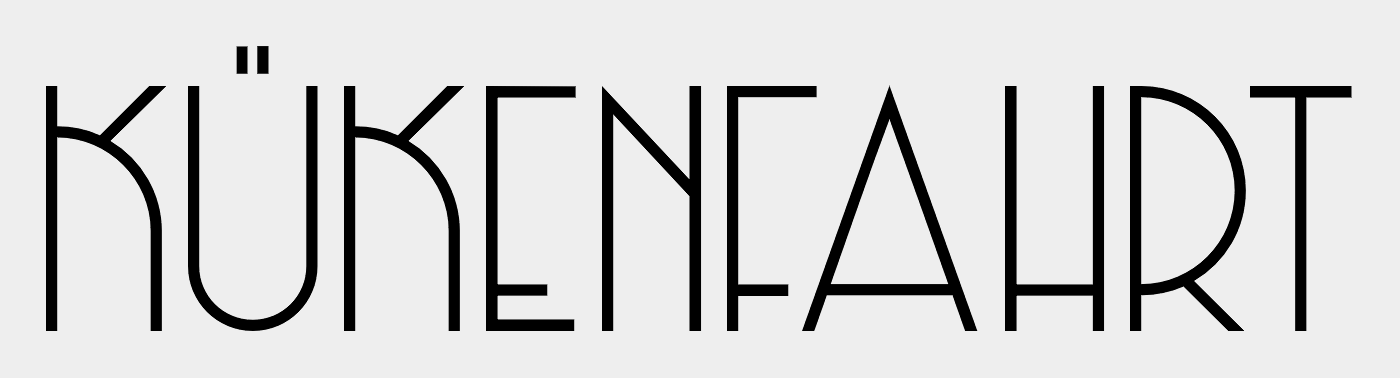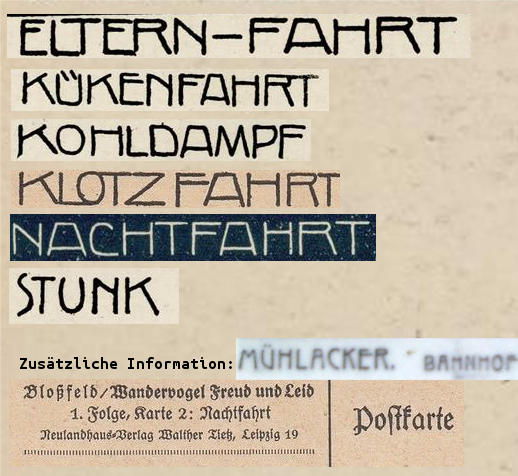
Suche: Satzschrift ca. 1920, Postkarten und Bild-Beschriftungen
leider komme ich bei der Suche - u.a. entsprechende der „ besten Tricks“ - nach einer Schriftart nicht weiter. Auch das Freistellen einzlner Buchstaben sowie das Entfernen der Unterschneidung hat für die Finde-Tools nichts gebracht. Besonders lässt mich Trick No9 zweifeln ob es sich überhaupt um eine „heute verfügbare Satzschrift“ handelt. Vielleicht kann mir hier jemand weiterhelfen.
Die ersten sechs Worte (siehe Grafik) sind und vermutlich vom selben Verfasser. Sie finden sich auf (Scherenschnitt!-)Postkarten aus den Jahren um/vor 1920 und stammen aus einem Verlag bei Leipzig. Ich bin mir sicher dass ich diese Art von Schrift jedoch auch auf gänzlich anderen Karten/Bildern gesehen habe.
Besonders markant finde ich die Buchstaben A,K, und R. Sowie die Höhe der Querstriche bei E,R und F. Das Bild mit dem Text „M… Bahnhof“ (eine Bildunterschrift) zeigt m.E. trotz Abweichungen eine sehr ähnliche Schrift, ist vermutlich jedoch ca. 5-10 Jahre später (und in Württemberg) entstanden. Die zusätzlichen Informationen habe ich für einen eventuellen Abgleich der Zeit hinzugefügt.
Da beide Quellen vermutlich handschriftlich sind frage ich mich ob es für diese beiden wohl eine gemeinsame Grundlage gibt. Ich bin für jeden Hinweis sehr dankbar.
Ich meine auch, diese Schrift (obwohl die in diesem Beispiel wohl handgezeichnet ist), schon einmal sehr ähnlich in einem früheren Strang (und auch sa sehr sicher handgeschrieben) gesehen zu haben.
Gut möglich, das die Schrift als Vorlage in einem Vorlagenheft für mit der Feder zu schreibende Werbeschriften, und dort sicherlich vom Autor ebenfalls handgeschrieben veröffentlich wurde. Ich habe ähnliche Anleitungshefte, herausgegeben von verschiedenen Schreibfedern-Herstellern und Tinten-Herstellern wie Brause und Pelikan, aber auch anderen Anbietern.
vielen Dank für die Antworten. Die Ähnlichkeit ist oft gegeben. Es sind tolle Schriftarten dabei. Leider sind die Abweichungen noch zu groß als das ich sie nutzen könnte.
Hat vielleicht noch jemand eine Idee?
Du hast ja selbst schon erkannt, dass das wohl Handschrift ist. Somit wirst du keine Satzschrift dazu finden, schon gar keine digitale. Die gezeigten Zeilen sind ja auch alle unterschiedlich.
Wenn du das als Schrift brauchst, wirst du es speziell für diesen Zweck erstellen lassen müssen.
Da gebe ich dir vollkommen recht. Ich hoffe jedoch hinsichtlich der Vorlage bzw. des Ursprungs dieser Schrift noch den ein oder anderen Hinweis zu bekommen. Im Hinblick auf das erstellen einer Schriftart fehlt mir für einige Buchstaben einfach noch die Idee dahinter.
Generell ist die schon auf meiner "to do" Liste, eigentlich schon länger, denn, wie gesagt habe ich die schon einmal gesehen (finde aber leider die andere Grafik nicht wieder) Das zar so eine K. u. K. Regiments-Sache, und was die fehlenden Buchstaben anbelangt, kann ich das aus dem Stil der Schrift schon recht schlüssig ableiten, ist also eigentlich nur ein Zeitproblem.